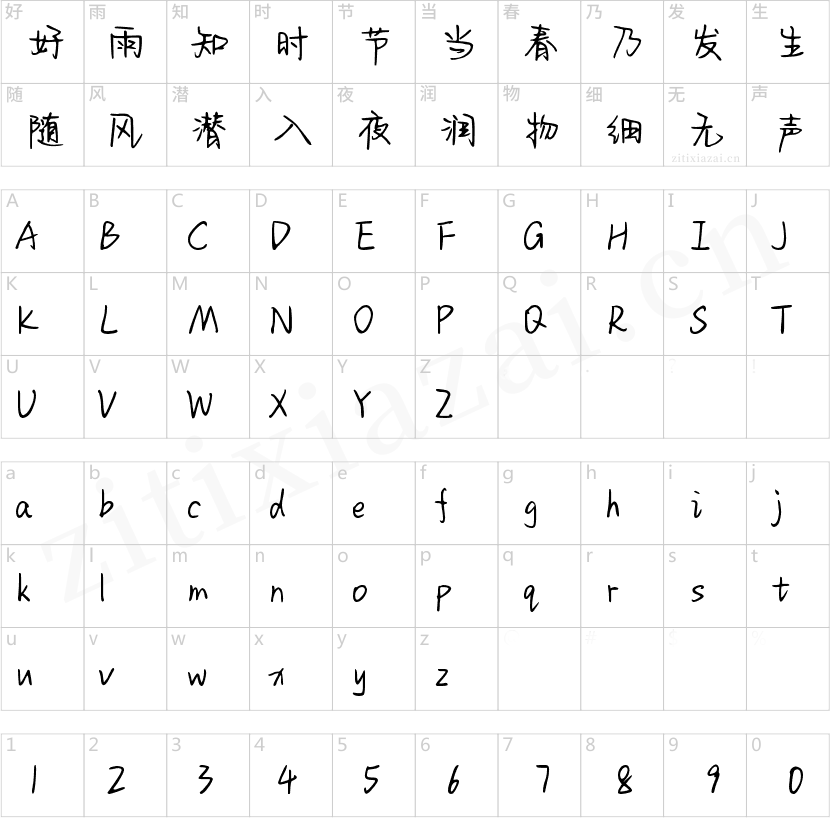
Aa日落跌进昭昭星野
Aa日落跌进昭昭星野字体
Aa日落跌进昭昭星野是一款非常具有艺术性的字体,它的设计灵感来源于对古典艺术的研究,同时又融入了现代字体设计的元素。字形优美,笔画粗细变化自然,给人以大气、典雅的感觉。Aa日落跌进昭昭星野是一款既传统又现代的字体,它的设计充满艺术感,美观大方,实用性也非常强。无论是对于设计师还是对于普通读者来说,都是一种非常不错的字体选择。Aa日落跌进昭昭星野适合用于具有艺术感的场合,比如海报、宣传单张、书籍封面等。由于其字形流畅且具有动态感,也适合用于大量的文本排版,如报纸、杂志等。